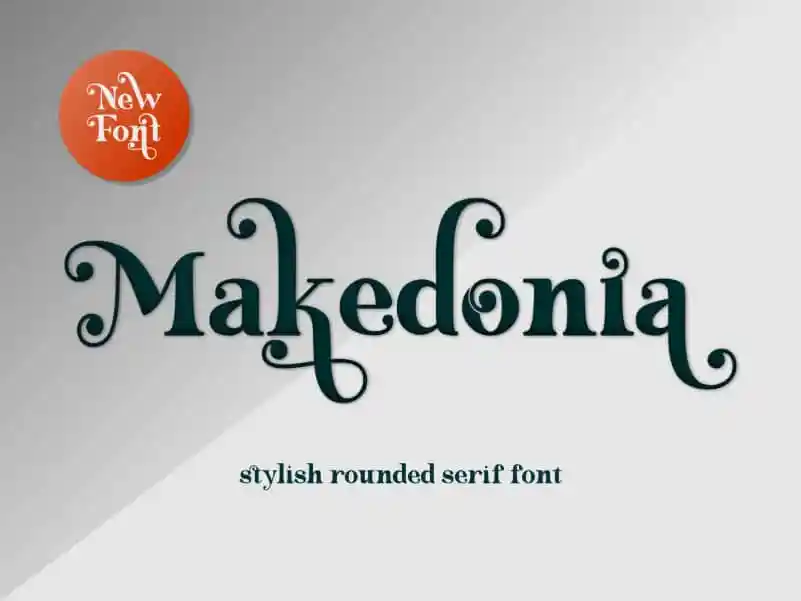
Makedonia Serif Font – Download Grátis
A Makedonia Serif Font é uma elegante e única fonte serif que traz para sua página a elegância sofisticada dos textos clássicos. Ela apresenta um traço de serif fino e arredondado, oferecendo um toque distintivo e moderno aos seus designs. Além disso, a fonte conta com três modos de decoração que você pode escolher de acordo com o seu gosto pessoal. Seja para dar um pouco mais de personalidade à sua página web ou impressa, a Makedonia Serif é uma opção perfeita para quem busca um toque sofisticado e único. Nuryanto Dwi, designer talentoso que criou esta fonte, certamente não podia estar mais satisfeito em ver seu trabalho se tornar parte do seu projeto.
Designer: Nuryanto Dwi